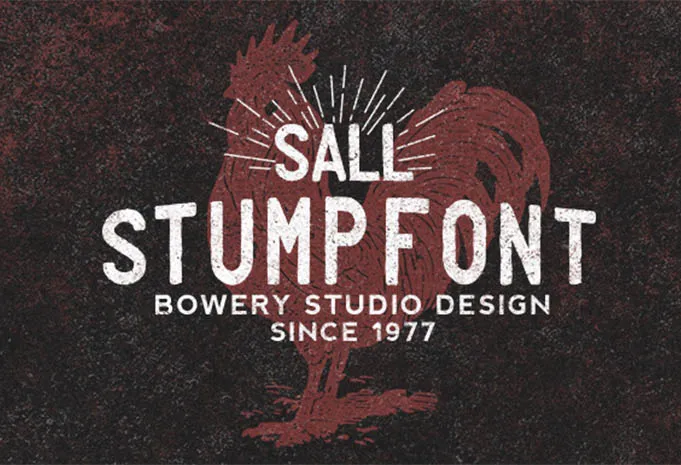
Stump Typeface – Fonte Grátis
Stump Typeface
Introduzimos Stump Typeface! Desenhada e compartilhada pela Bowery Studio Design, Stump é uma família de tipo com quatro faces que apresenta uma rara escrita vintage única e perfeita para headlines de todos os tamanhos, gráficos impressos, logotipos, selos, camisetas e projetos de design em geral. Seu estilo antigo e desgastado é perfeito para criar elementos visuais atraentes que se destacam em qualquer plataforma de design. Estamos ansiosos para experimentar Stump Typeface em seus próximos projetos!